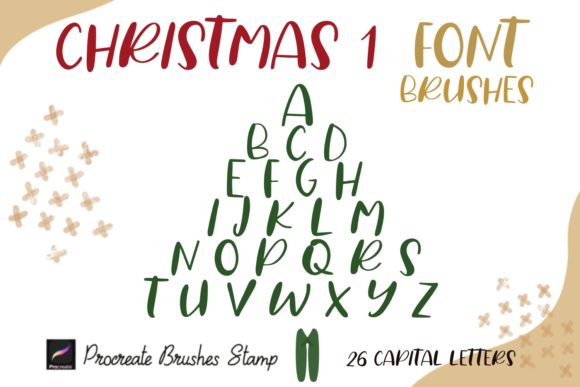
Procreate Brushes Stamp Christmas 1 Font
Die richtigen Designelemente zu finden, kann eine Herausforderung sein, aber Procreate Brushes Stamp Christmas 1 Font bietet eine außergewöhnliche Sammlung, die Ihre Arbeit sofort aufwertet.
Mit Präzision gefertigt, bietet Procreate Brushes Stamp Christmas 1 Font saubere Vektoren, eine reibungslose Typografie und eine kommerzielle Lizenz für ein beruhigendes Gefühl.
Egal, ob Sie POD-Produkte (Print on Demand), Hochzeitseinladungen oder Social-Media-Grafiken erstellen, Procreate Brushes Stamp Christmas 1 Font ist die ideale Wahl.
Experten-Tipp: Kombinieren Sie diese Elemente mit ergänzenden Schriftarten, um einzigartige, auffällige Designs zu kreieren.